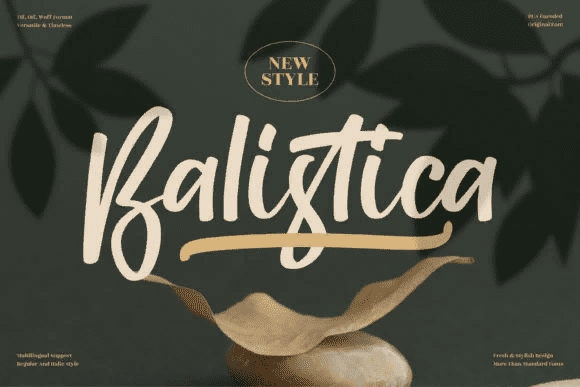
Название: Balistica Font (2021)
Balistica - это прекрасный и нежный шрифт, который излучает элегантность и класс.
Этот шрифт был создан специально для тех, кому нужен красивый и освежающий вид их дизайна.